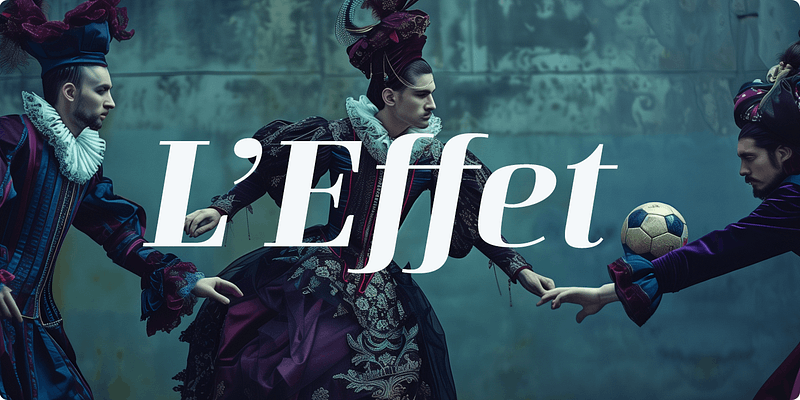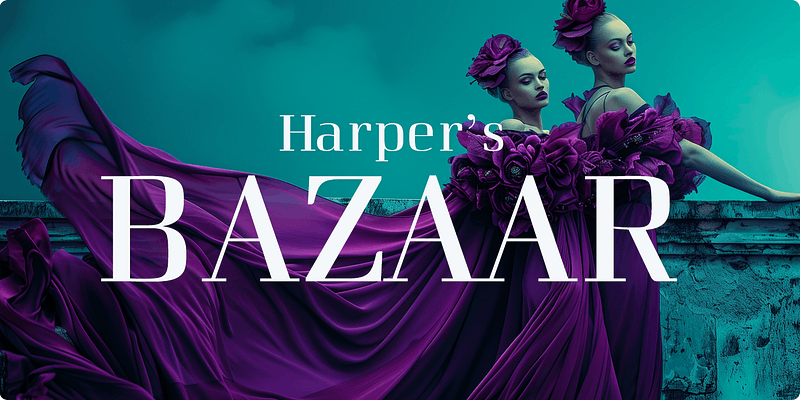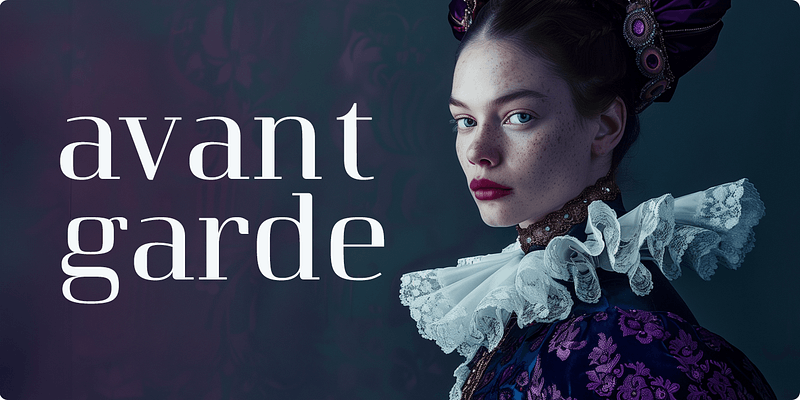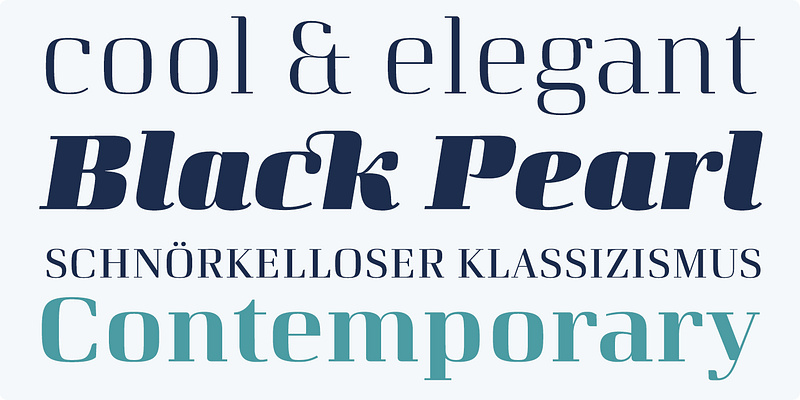
Curve er en moderne neo-klassisk skrifttypefamilie med nogle kendetegn fra Didone-genren, men specielt designet til moderne typografi.
En stor x-højde skaber ikke kun plads i bogstaverne til ekstra fede stile, men giver også Curve en åben og generøs karakter i de mere smalle og halvfede versioner.
Den har 616 glyffer med kapitæler, tal og ligaturer i 10 vægte.
Curve er en moderne serif-skrifttype, der er specielt designet til logoer, brands, magasiner og redaktionelt indhold og til at understrege trends inden for mode og design.